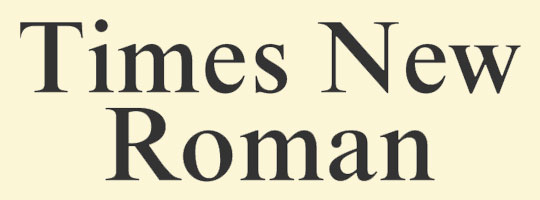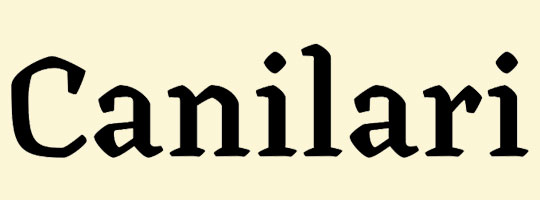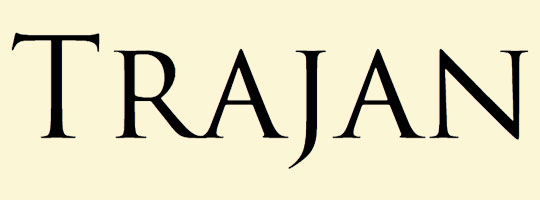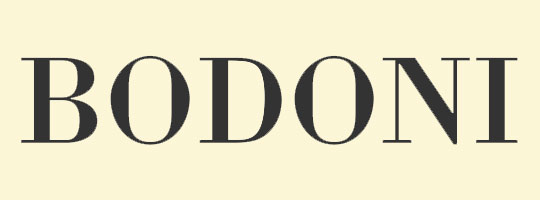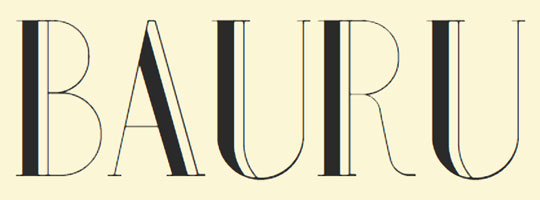
20 потрясающих шрифтов для дизайна логотипов, которые нужны каждому хорошему дизайнеру
Опубликовано: 2020-07-18Разработка логотипа может доставить вам много хлопот, особенно если вы хотите, чтобы он выглядел хорошо сбалансированным и всеобъемлющим. Одним из наиболее важных элементов, который есть почти в каждом логотипе, является типографика, которая выражает точную информацию о компании, о которой должны знать клиенты. Поэтому типографика заслуживает большого внимания при продумывании будущего логотипа.
Несомненно, наличие хорошо разработанного логотипа для визуальной идентичности бренда является главным требованием для любого бизнеса. Он состоит из цветов, форм, шрифтов и многих других элементов дизайна, которые делают его привлекательным. Правильное использование этих элементов придает вашему бренду творческую и уникальную индивидуальность, которая выделяет вас среди конкурентов.
Среди этих многочисленных элементов дизайна одна вещь, о которой всегда беспокоятся дизайнеры, — это выбор шрифтов для дизайна бизнес-логотипа. В Интернете доступны тысячи шрифтов, и среди тех шрифтов, которые выглядят привлекательно, трудно выбрать.
Какую принадлежность они привнесут в абстрактный стиль? Какие предположения они сделают о вашем имиджевом персонаже, подверженном этому? Чтобы ответить на эти просьбы, которые являются лишь следом чего-то большего, мы собрали эти советы и правила, чтобы помочь вам выбрать стиль содержимого пользовательского логотипа, который явно подходит вам. Изучите, чтобы найти шрифты, которые лучше всего подходят для вашего изображения.
Будучи наиболее важным фактором всего пользовательского дизайна логотипа, единственная ошибка в его выборе может сломать ваш дизайн. Итак, вы должны определить один или два лучших шрифта, которые идеально смотрятся в дизайне вашего логотипа и отражают профессионализм бренда. Итак, давайте обсудим некоторые из лучших шрифтов, которые вы можете использовать в своем логотипе и сделать его привлекательным.
1. Абель
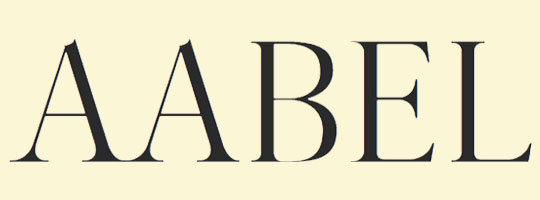
Aabel относится к категории шрифтов с засечками. Этот современный шрифт выглядит эстетично в дизайне вашего логотипа и особенно подходит для роскошных и модных брендов.
На самом деле, он поставляется с тремя весами: обычным, жирным и легким. Все эти версии красиво смотрятся в прописных и строчных буквах. Не только в бизнес-дизайне логотипа, этот шрифт подходит для плакатов, заголовков, рекламы, дизайна упаковки, книг и многих других мест. Любая комбинация шрифтов с этим отлично смотрится в вашем логотипе, поэтому его использование не будет неправильным выбором.
2. Гарамонд
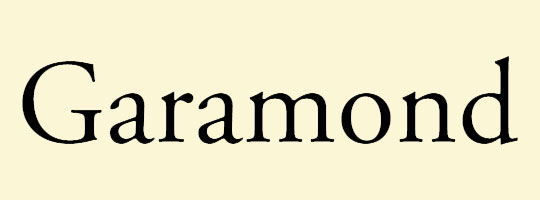
Garamond — один из старейших шрифтов с засечками, появившийся в 16 веке. Воспользуйтесь преимуществами этого шрифта, добавив свой индивидуальный дизайн логотипа, он придает элегантный вид. Продемонстрируйте индивидуальность и профессионализм вашего бренда с помощью этого шрифта, используя его в логотипе.
Первоначально он был вдохновлен ударами Клода Гарамона; в настоящее время вы можете получить множество вариантов этого конкретного шрифта. Самым популярным является Adobe Garamond, разработанный Робертом Слимбахом. Из-за удобочитаемости он также используется в журналах и газетах.
3. Роквелл
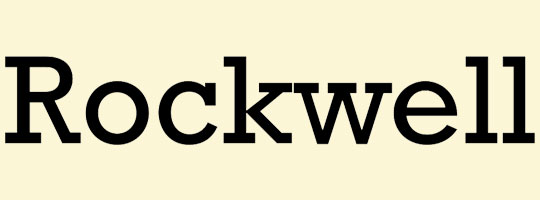
Еще один лучший шрифт логотипа, который сделает ваш дизайн еще более привлекательным. Он относится к семейству шрифтов с засечками. Хотя он был разработан в 1934 году, в настоящее время он находится в центре внимания и может использоваться в дизайне бизнес-логотипа.
Он использовался в информационных вывесках на выставке Expo 86, легкорельсовый транспорт Доклендс использовал жирный вес Роквелла в 1980-х годах. Из-за моновзвешенного хода он в основном используется в небольших размерах.
4. Фрутигер
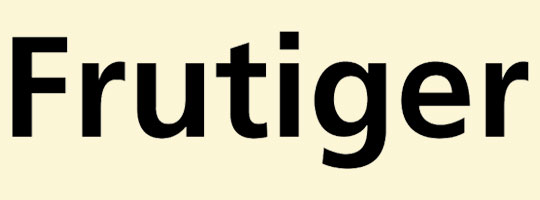
Шрифт с лучшей разборчивостью даже при небольшом размере. Таким образом, вам не нужно беспокоиться, если ваш дизайн логотипа используется на любом размере экрана или в любом месте. Он был разработан Адрином Фрутигером, дизайнером шрифта Univers. Поскольку дизайнер из Швейцарии, он используется в швейцарском паспорте с 1985 года.
При планировании предков шрифта Concorde и Roissy цель Фрутигера состояла в том, чтобы создать шрифт без засечек с проницательностью и аккуратностью Univers, но с естественными и относительными частями Gill Sans.
Таким образом, чтобы ваш логотип хорошо читался в маленьком и большом приложении, этот шрифт был бы лучшим выбором.